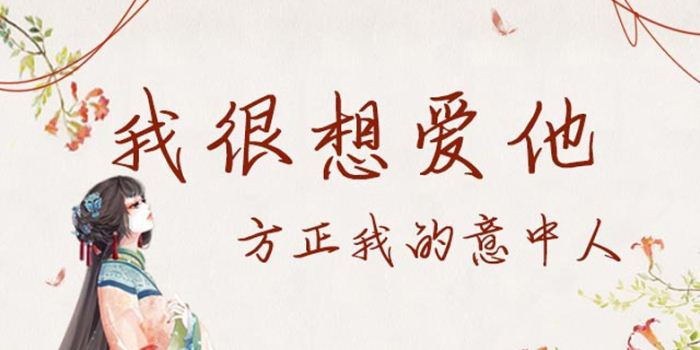
方正手跡-我的意中人由方正字庫(kù)余丹設(shè)計(jì)師出品的藝術(shù)字體,該字整體斜向右上方,左低右高,筆畫(huà)收緊轉(zhuǎn)折銳利,適合應(yīng)用于藝術(shù)設(shè)計(jì)、平面宣傳設(shè)計(jì)、網(wǎng)頁(yè)設(shè)計(jì),書(shū)法等領(lǐng)域。
我的意中人是一款文藝十足的手寫(xiě)體。該字體整體斜向右上方,左低右高,筆畫(huà)收緊轉(zhuǎn)折銳利,整體給人硬朗緊致的感覺(jué)。適用于文藝類(lèi)的書(shū)刊、品牌廣告和產(chǎn)品包裝設(shè)計(jì),以及社交網(wǎng)絡(luò)的個(gè)性化用字。。